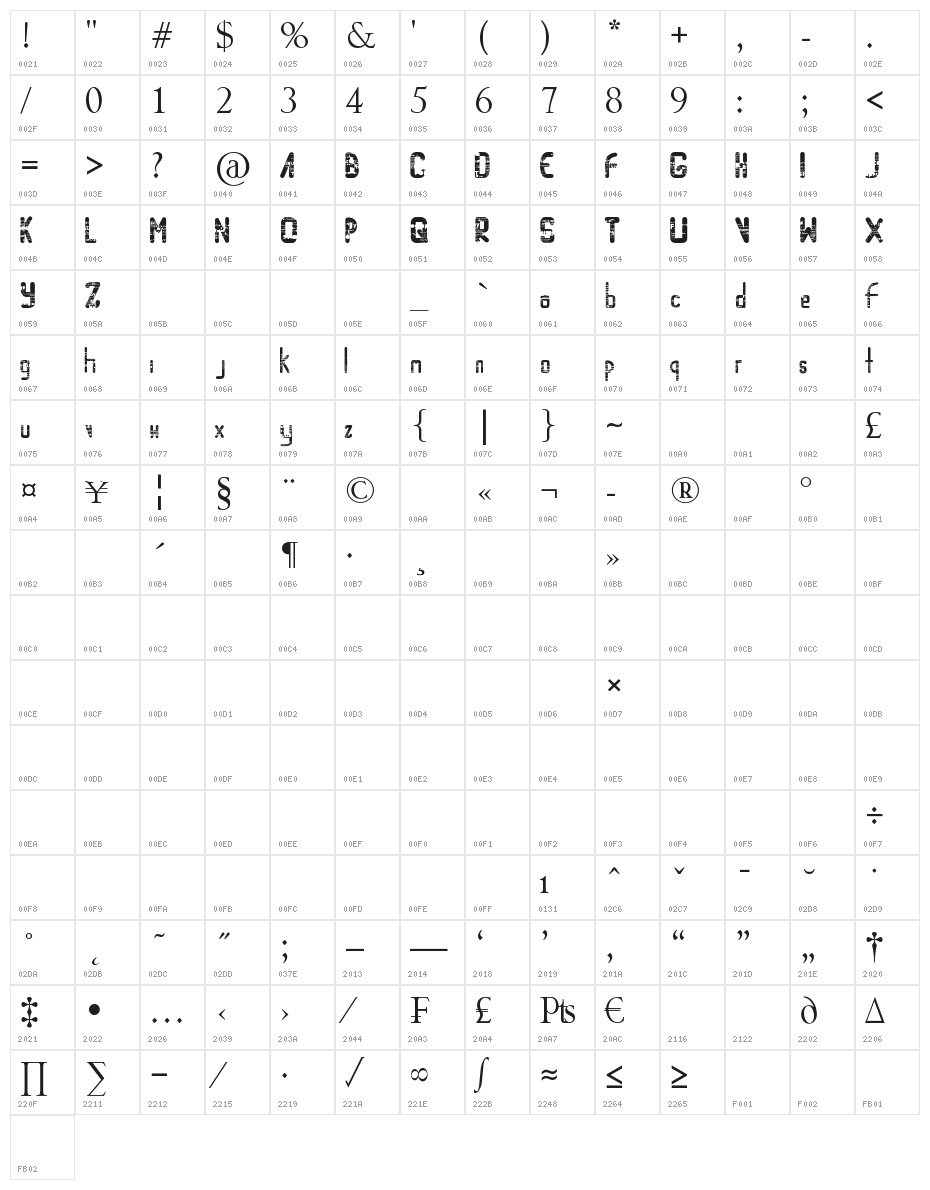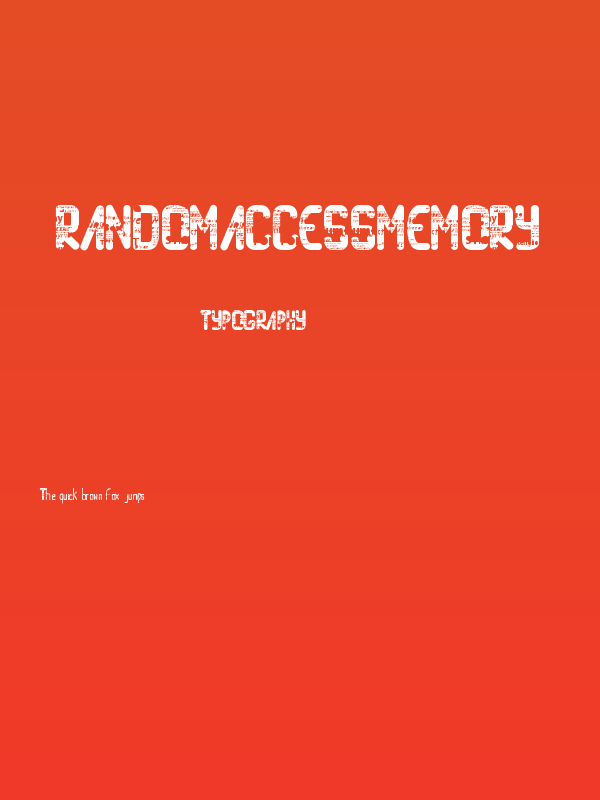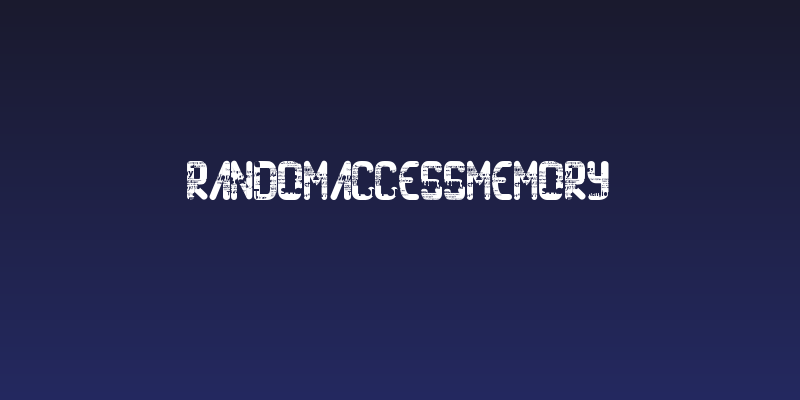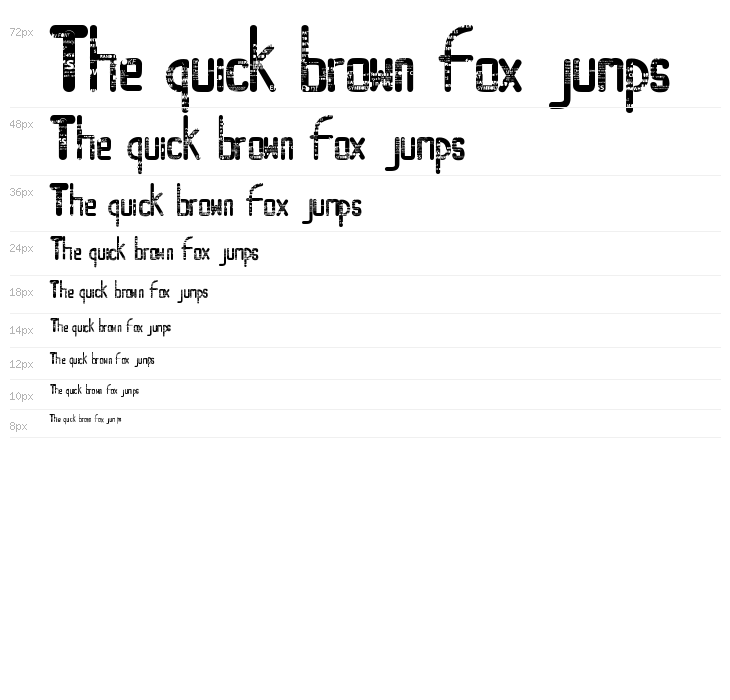
RandomAccessMemory Font
| श्रेणियाँ | Decorative |
| समग्र शैली | Modern, Vintage |
| उपयोग का मामला | Logos, Headlines, Posters |
| सुझाए गए प्रोजेक्ट | Ideal for digital art, music album covers, posters, and edgy branding projects. |